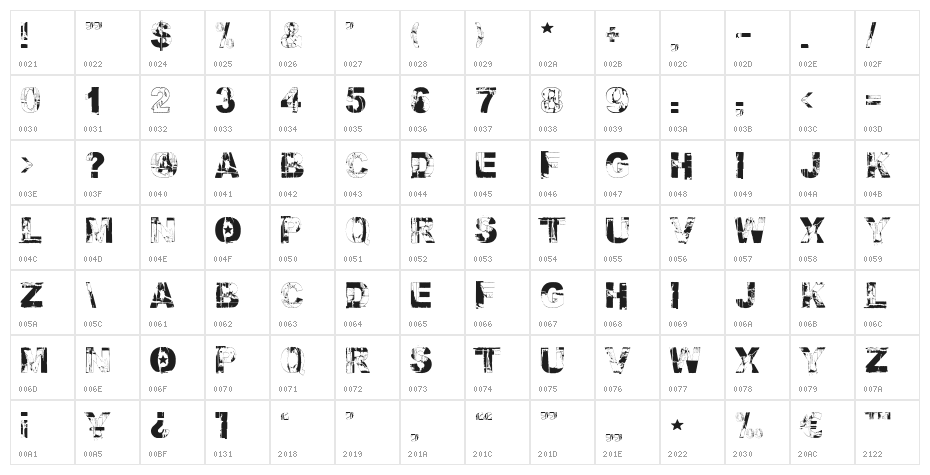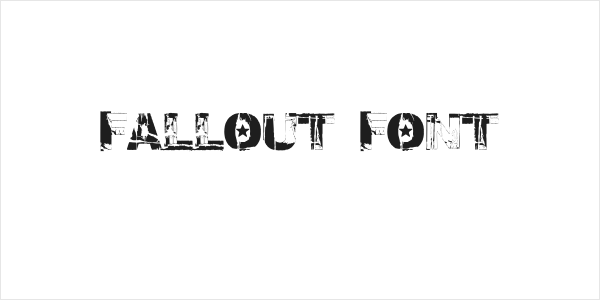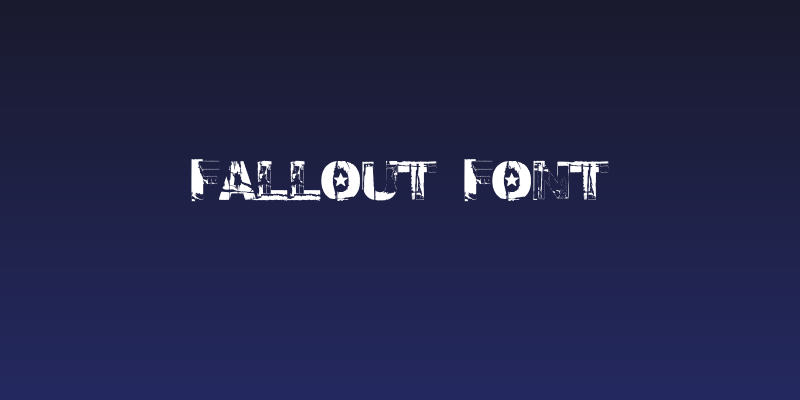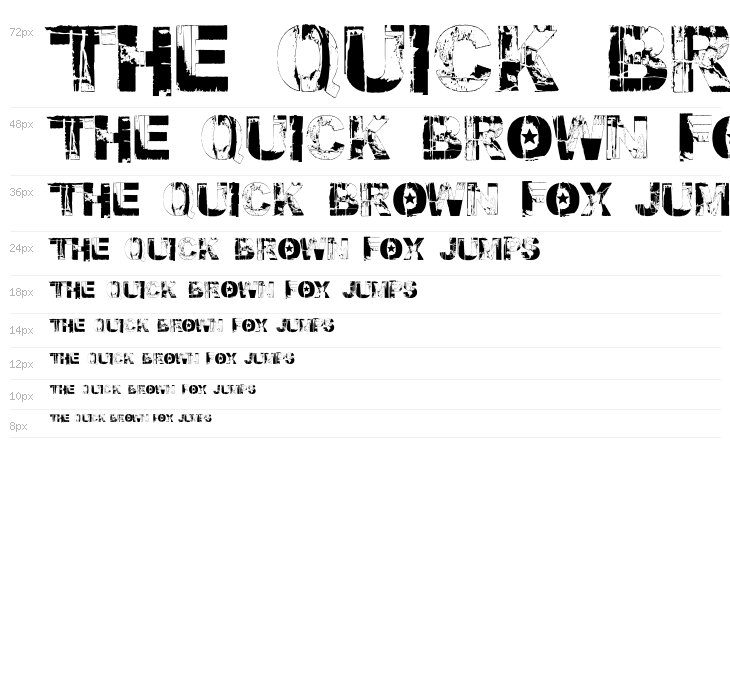
Fallout Font Font
| Vorgeschlagene Projekte | Ideal for video game titles, movie posters, or any design needing a post-apocalyptic or industrial theme. |